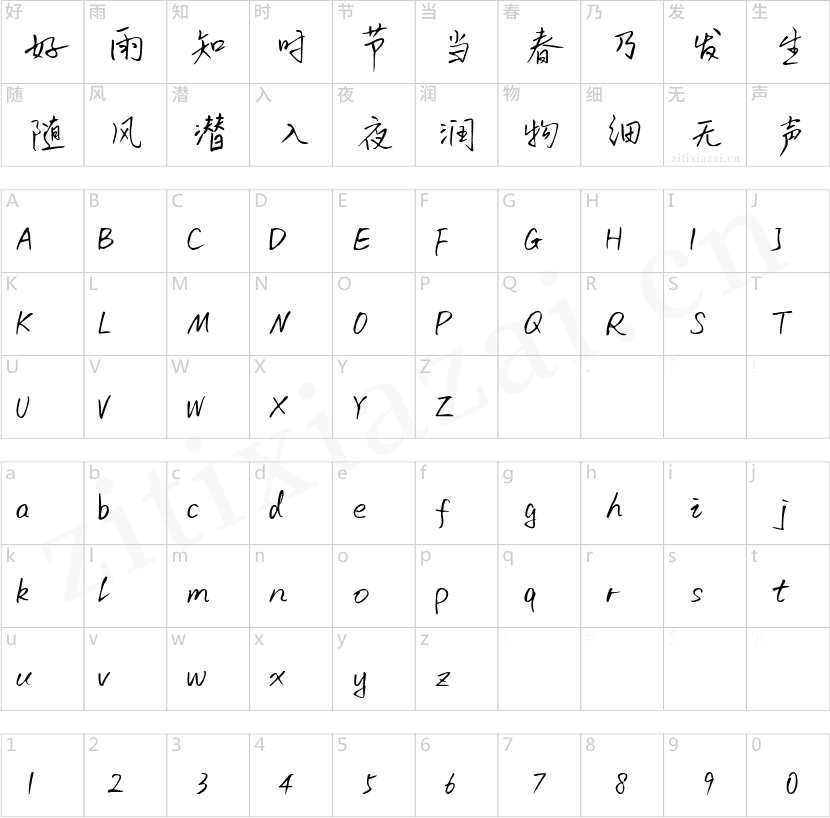
字魂初林体
字魂初林体,这款字体结构工整、笔画清晰,兼顾美观与易读性,适用于标题、正文、海报、包装、LOGO 等多种场景。字形优雅稳定,风格百搭耐看,适配日常排版与创意设计,让文字呈现更舒适、更具质感。字魂初林体一笔一画,皆是细节,以均衡的比例、流畅的线条打造舒适视觉体验,字形端正大气,风格简约现代。无论是商业设计、品牌宣传还是日常排版,都能轻松驾驭,让文字更有格调与力量。字魂初林体字体下载。